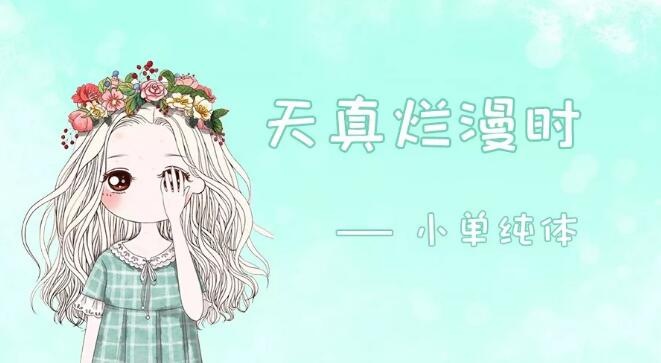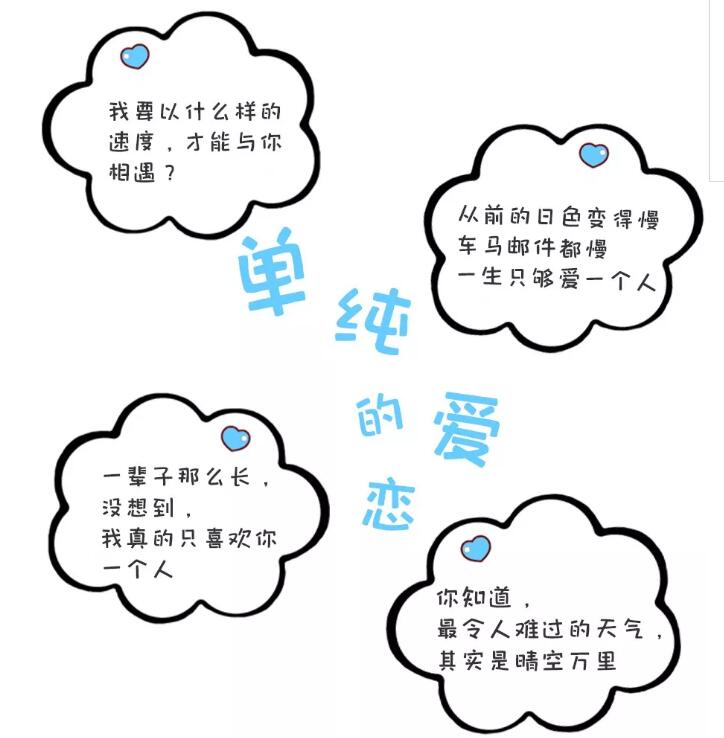
小单纯体
小清新系列第一弹~~~小单纯体
天真烂漫的色彩,简简单单的感觉,扑通扑通的心跳,甜甜蜜蜜的初恋。
这就是,小单纯体。
为了设计小单纯体,设计师搬出了好多初恋的故事,看故事的她,有时哭,有时笑,总是一脸陶醉的模样。就这样,又重温了一遍懵懂时候那些单纯的小美好。
第二天醒来,那种感觉似乎更加香醇,久久都未散去。坐在电脑面前,脑子里蹦出的是这几个词:简单纯粹、踏实、甜美。
这就是小单纯体的由来。
小单纯的世界,简单纯粹。
有的人,从小就和你一起上学,一起自习,一起玩耍。早上给你准备好热腾腾的早餐,中午找一个安静草地沐浴阳光,晚上总不忘和你说晚安。
简单而纯粹,没有过多的修饰。为了体现这样的感觉,小单纯体在字形上去除了折笔的弧形,换之以平直的笔画,竖弯钩转为竖折,同时弱化钩笔画,省去了许多笔画末尾的小尾巴,显得更加干净精巧。
小单纯的世界,很踏实。
初恋的感觉很踏实。或许是那时的我们还很单纯,没有太多现实因素的干扰,感觉一生真的只够爱一个人。